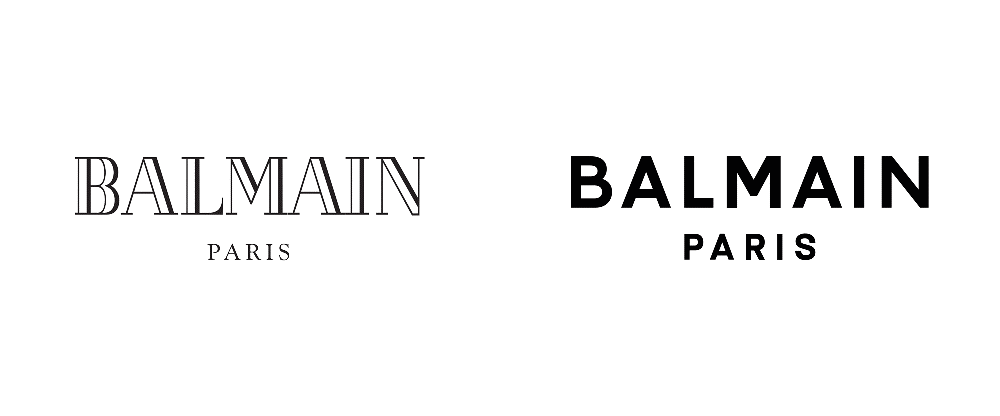
Fino ai primi anni 2000 il mondo è stato tutto fronzoli e ghirigori, poi la svolta minimal ha inondato ogni angolo, andando a toccare tutti, ma proprio tutti, anche i più grandi marchi di moda. Soffermiamoci un secondo a guardare come sono cambiati i loghi dei marchi di moda negli ultimi anni, non sembra che si stiano tutti uniformando? Perché tutti sembrano utilizzare gli stessi font e rispecchiare le stesse caratteristiche?
Tutti prima o poi si rifanno il look, soprattutto i grandi marchi di moda. È il rebranding di un’azienda, cambia la loro visione e così si mostrano al mondo in maniera diversa. Solitamente il cambio del logo coincide con l’arrivo di un nuovo direttore creativo o con le esigenze del mercato. E allora ci viene da chiedere come mai i loghi dei marchi di moda stanno diventando tutti uguali?
Le caratteristiche dei loghi di molti marchi di moda
Molti marchi di moda si sono uniformati sulla stessa tipologia di logo. Troviamo Saint Laurence, Burberry, Calvin Klein, ecc.
I canoni che si seguono per la creazione dei nuovi loghi sono semplici ed essenziali, non abbandonando mai la svolta minimal. I font utilizzati sono i Sans Serif, geometrici e naturali, la tipografia utilizzata è il maiuscolo. Hanno ridisegnato il proprio stile semplificandosi, per alcuni troppo. Tutti sono cambiati dal 2010 in avanti e in molti se ne stanno rendendo conto e si stanno domando perché.
“Interesting logos are being replaced by boring ones”, fa notare BoingBoing, la cui opinione, ovviamente, è contraria a questa svolta minimal dei loghi dei marchi di moda.
Ma quelli che si sono domandati il perché di questo cambiamento hanno anche cercato di dare una risposta.
Perché i loghi sono diventati tutti uguali?
Ecco le motivazioni che secondo alcuni hanno dato origine a questo cambiamento, a questa uniformazione dei loghi dei marchi di moda.
- I millenial sono no-logo: i millenial sono la generazione che ora si ritrova ad acquistare. Ed è a loro che il mercato deve rivolgersi. Bombardati sul finire del ‘900 da una moda pesante, che dettava legge e che tutti seguivano senza domandarsi il perché, quello che si cerca oggi è qualcosa di diverso. Le nuove generazioni non accettano la moda passivamente come una volta, ma ne sono parte integrante. Sembra, quindi, che i millenial preferiscono loghi invisibili, passando essi inosservati sono loro a scegliere e non la moda a scegliere per loro.
- Globalizzazione: ovviamente la globalizzazione gioca un ruolo fondamentale in tutto ciò. Il mercato è divenuto globale, per ciò anche la moda deve adattarsi e perdere un po’ di quel suo patriottismo da vecchio continente.
- Il digitale: infine, non dobbiamo mai dimenticarci che oggi viviamo ormai costantemente connessi. I loghi devono adattarsi quindi a esigenze diverse, come quelle delle app, dei social e dei siti internet, che prediligono font minimal.
Alcuni marchi di moda che hanno ridisegnato il proprio logo minimal
Vediamo ora nel concreto di cosa stiamo parlando. Parliamo, ad esempio, di Saint Laurence, che nel 2012 ha ridisegnato il proprio logo. Il cambiamento coincide con l’arrivo di un nuovo direttore creativo, Hedi Slimane. A cambiare non è solo il logo, che si veste con un font Helvetica proveniente dagli anni ’60, ma il nome stesso che passa da Yves Saint Laurence a Saint Laurence.
Calvin Klein cambia logo nel 2017, passando da un corsivo a uno stampatello marcato. E, per ricordare il mondo digitale in cui viviamo, il logo è stato annunciato su Instagram.
Passiamo, poi, a Burberry, che ha completamente sconvolto il proprio logo. Innanzitutto è sparito il cavaliere presente sin dal 1901, e il logo diventa un sans serif geometrico e minimalista.
Infine, anche Celine ha rivisitato il proprio logo. Sebbene esso era già discreto e minimal nella precedente versione in questo nuovo logo scompare l’accento, rendendolo così più internazionale.